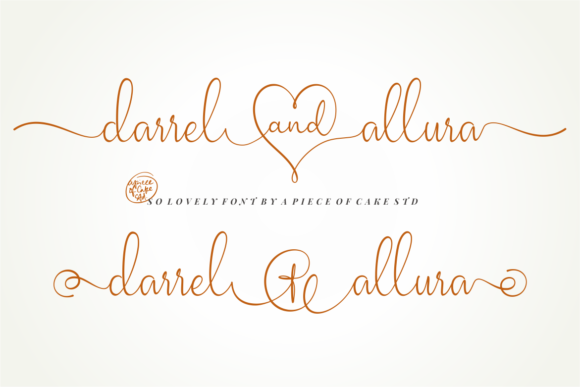
Darrel Allura
Darrel Alluraのような高品質の素材をお探しの場合、このプレミアムパッケージはクリエイティブなプロジェクトに素晴らしい選択です。
精密に作られたDarrel Alluraは、クリーンなベクター、滑らかなタイポグラフィ、そして安心のための商用ライセンスを提供します。
POD(オンデマンド印刷)製品、結婚式の招待状、またはソーシャルメディアのグラフィックを作成している場合でも、Darrel Alluraは理想的です。